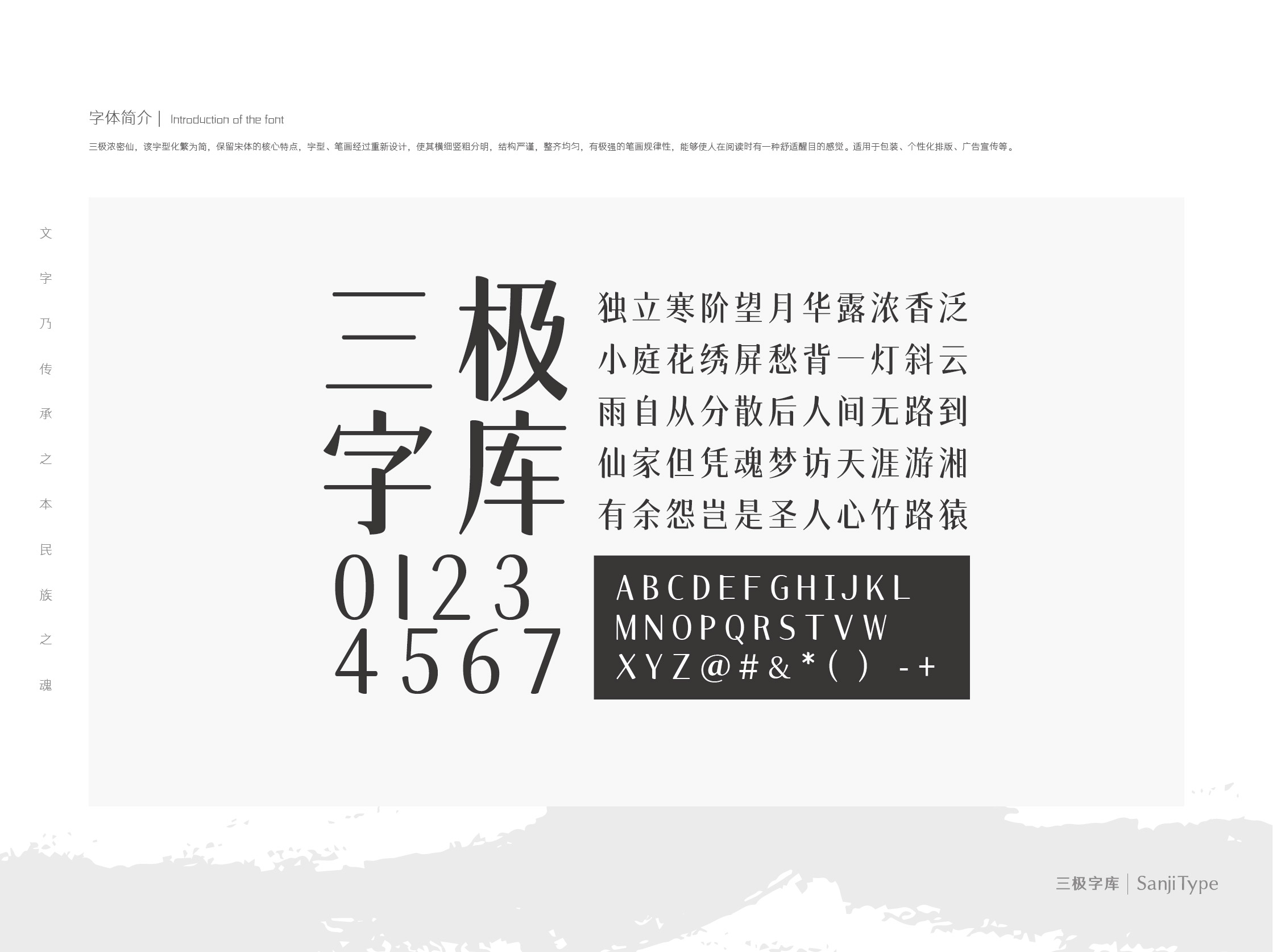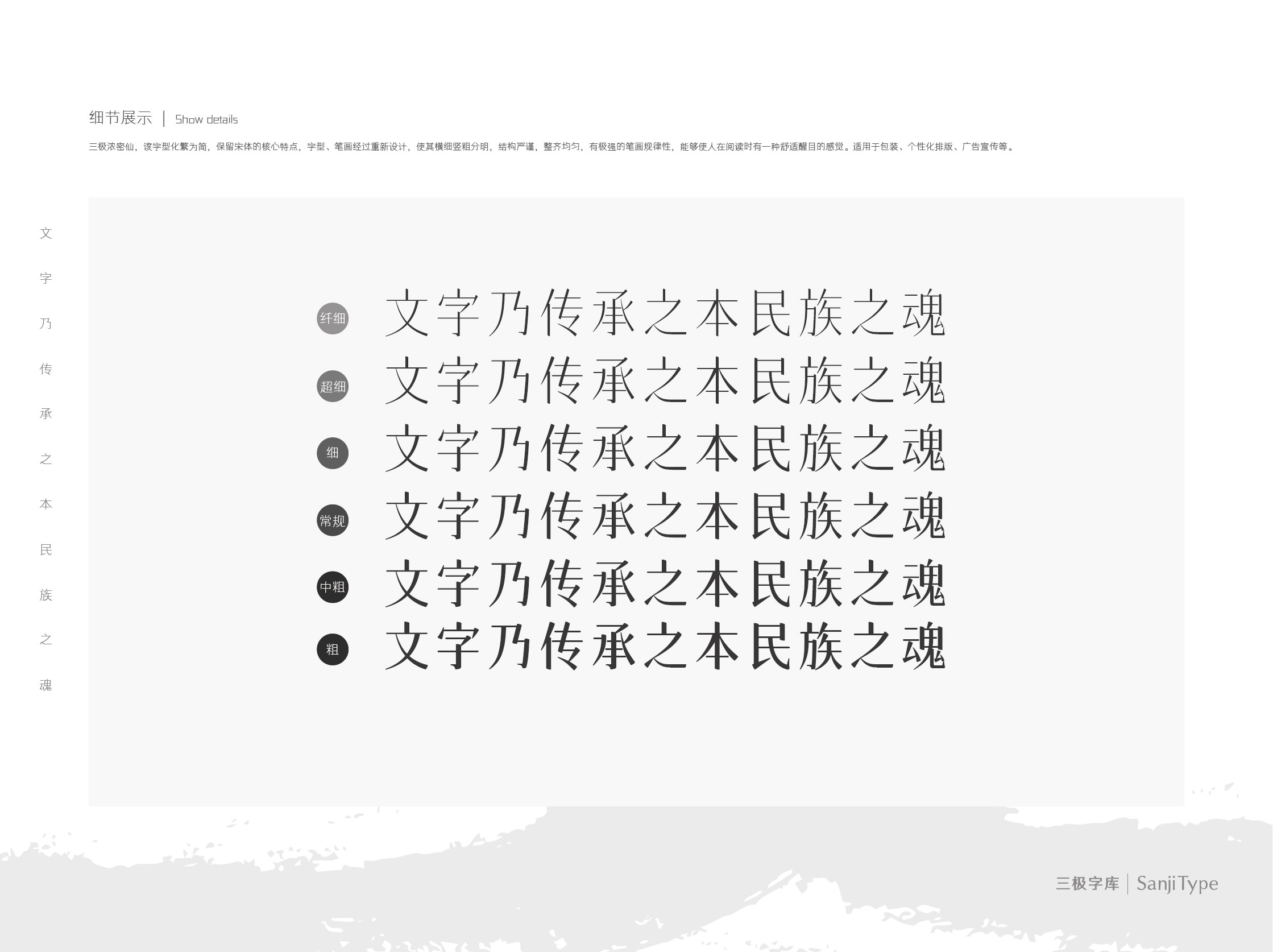
三极浓密仙家族
三极浓密仙 超细
三极浓密仙 纤细
三极浓密仙 细
三极浓密仙 中粗
三极浓密仙 粗
三极浓密仙
三极浓密仙,该字型化繁为简,保留宋体的核心特点,字型、笔画经过重新设计,使其横细竖粗分明,结构严谨,整齐均匀,有极强的笔画规律性,能够使人在阅读时有一种舒适醒目的感觉。适用于包装、个性化排版、广告宣传等。